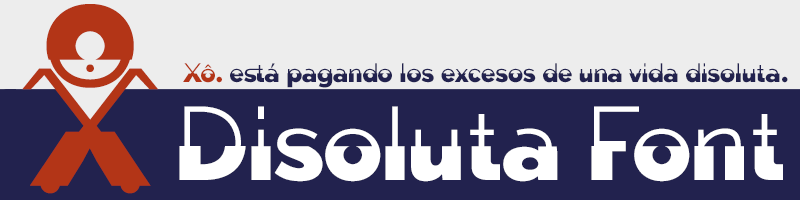
A Disoluta é uma experimentação tipográfica que resultou na fusão de duas fuentes sans-serif diferentes pesos. O designer Hamilton utilizou suas próprias anteriores fuentes: Tabarra Black e Light para criar essa abordagem original, oferecendo um equilíbrio interessante entre força e delicadeza. Esta fonte tem um carácter elegante que não deixa de ser moderna, com linhas retas e uma forma minimalista que se adequam bem a textos em diversos formatos gráficos. Ideal para criar um design contemporâneo e sofisticado, a Disoluta é perfeita tanto para aplicações web quanto impressão digital ou física. Seja você criador de sites, designer editorial ou ilustrador, este é um recurso útil que certamente enriquecerá seus trabalhos digitais.